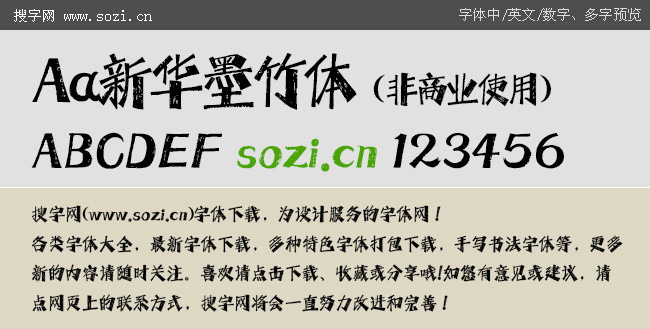
Aa新華墨竹體
搜字網(wǎng)給大家提供一款A(yù)a新華墨竹體(非商業(yè)使用)中文字體下載,該字體是一非常有個性的藝術(shù)字體,風格比一般的字體更有特,字跡清新簡明,具有很好的視覺感,適用于平面宣傳設(shè)計、網(wǎng)頁設(shè)計、海報設(shè)計等應(yīng)用(此字體為個人非商用版,商用可以聯(lián)系QQ:1006760504)。